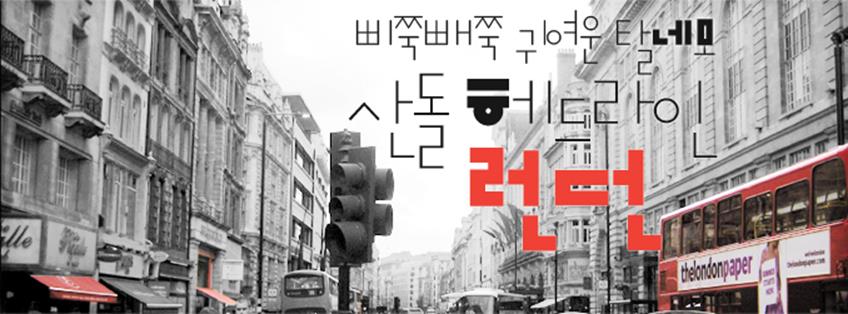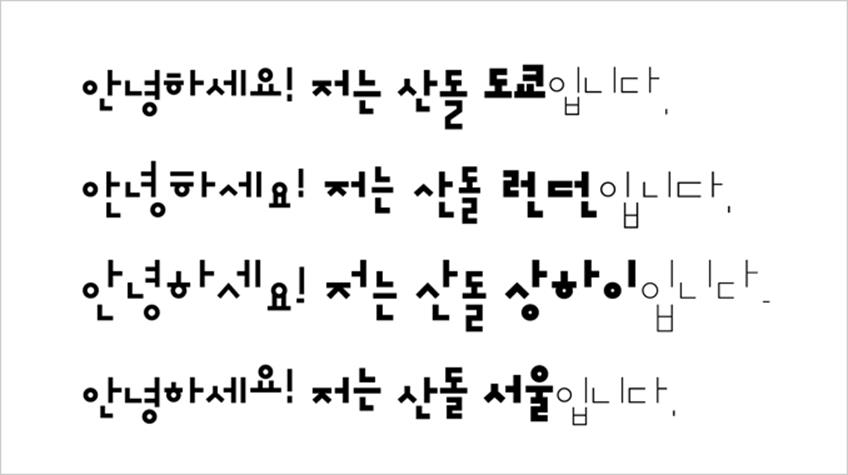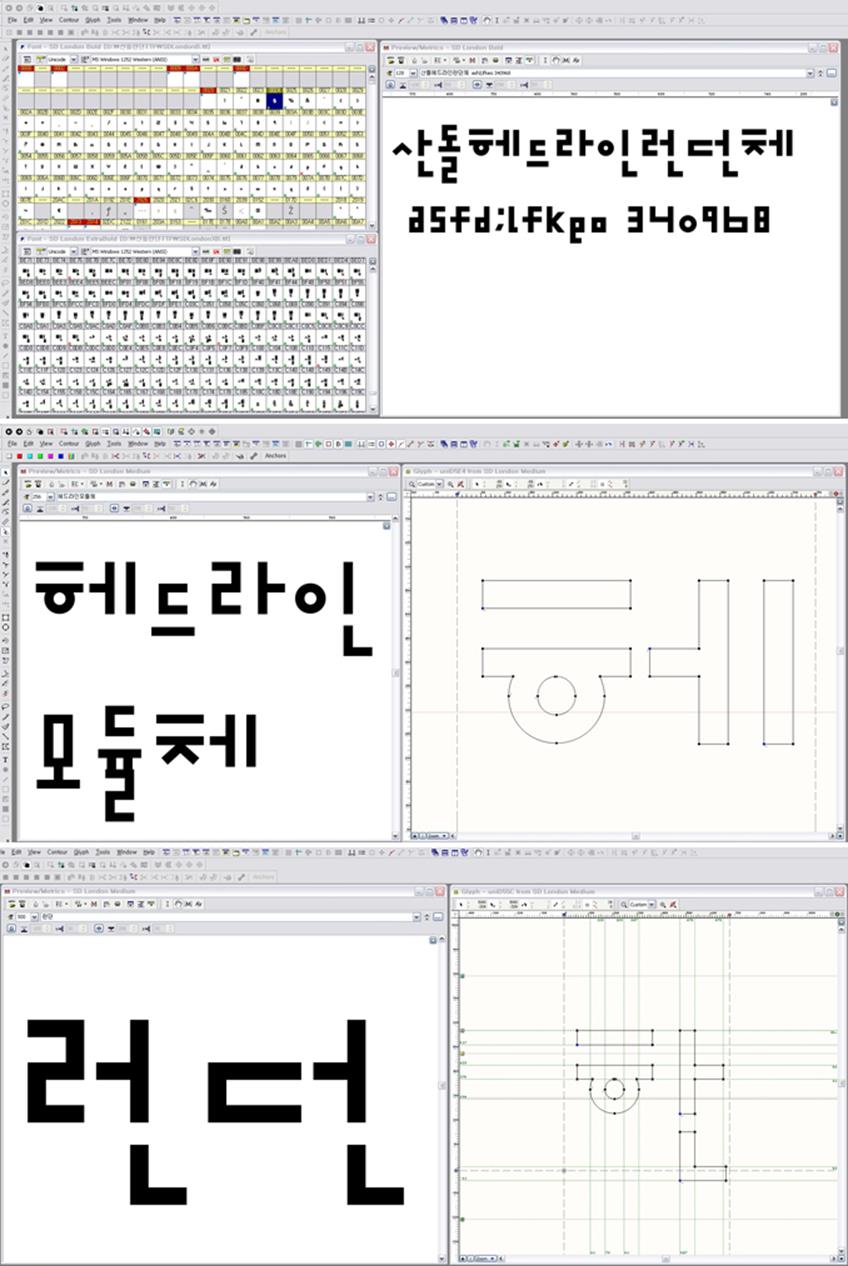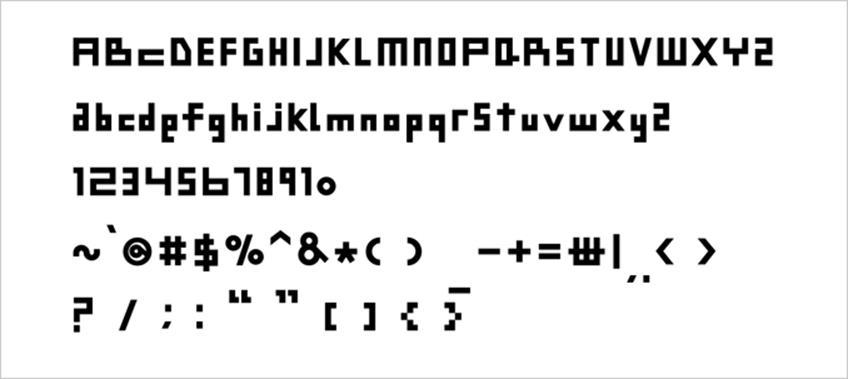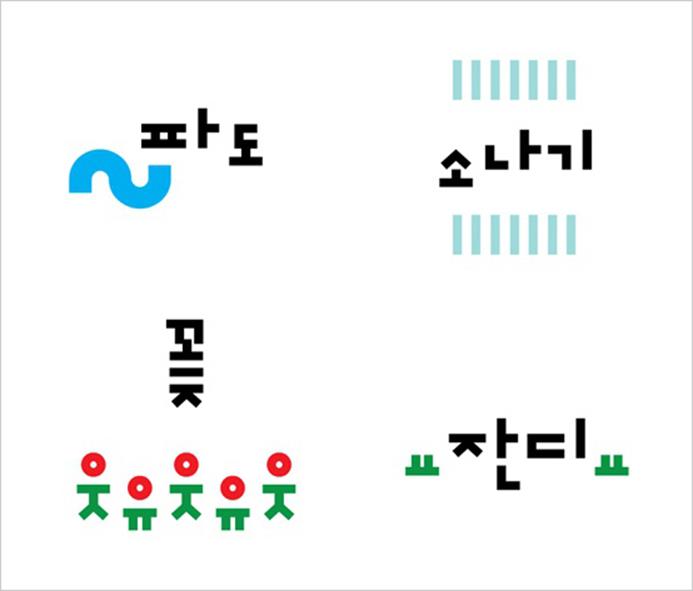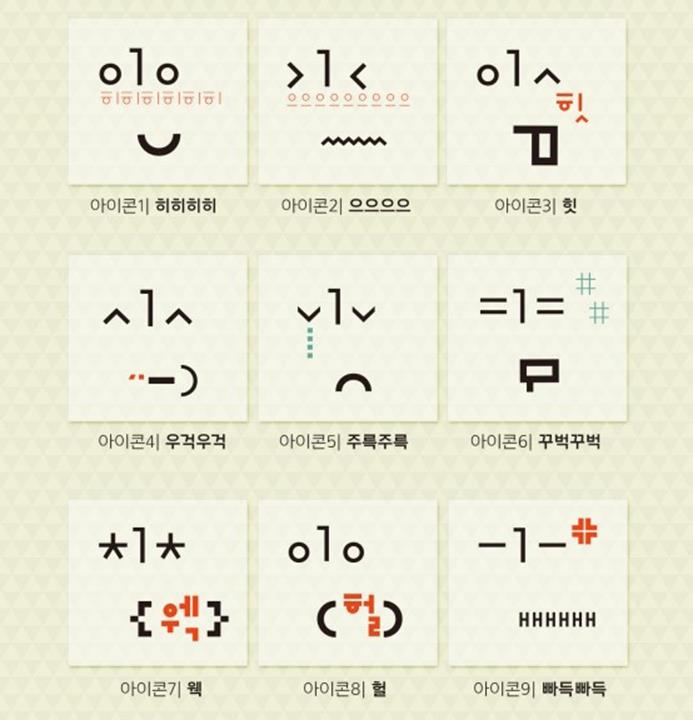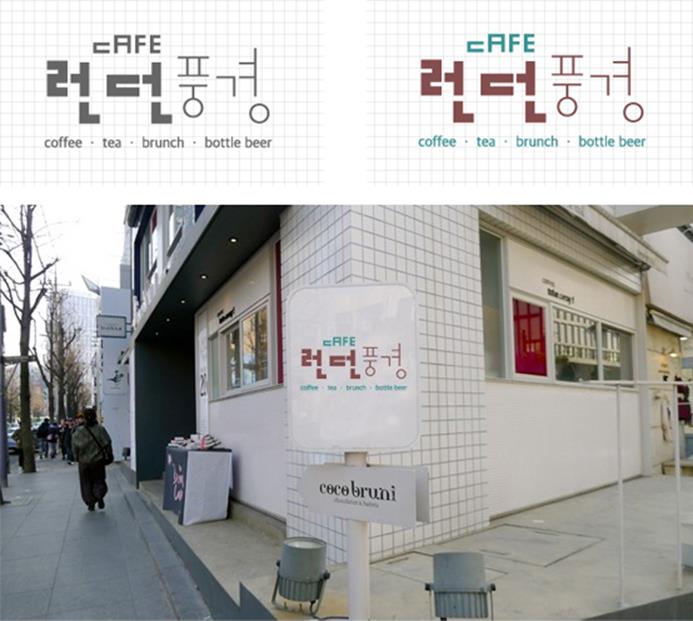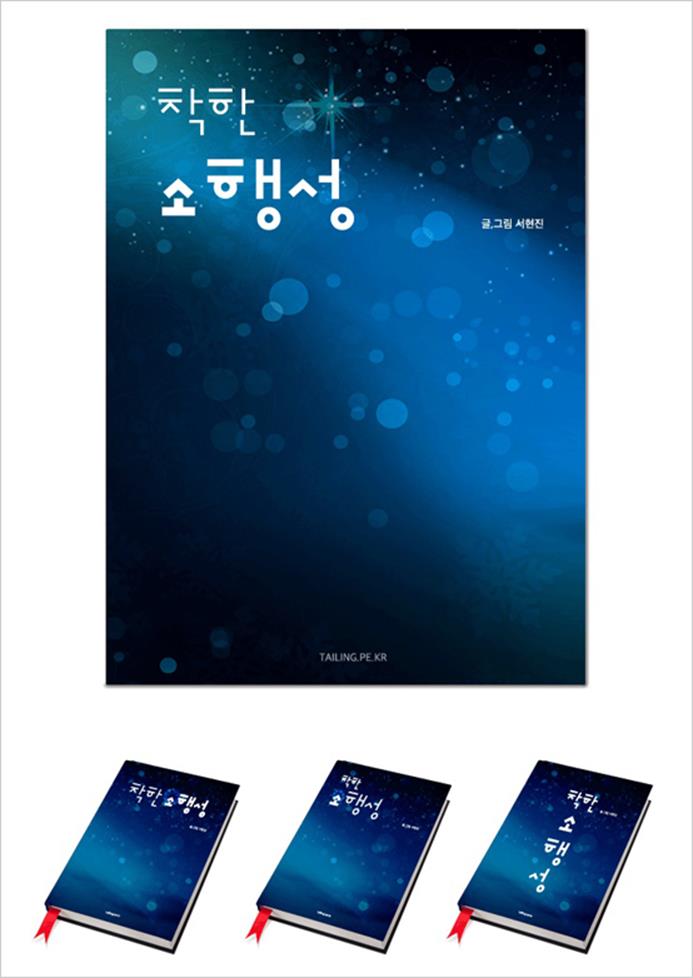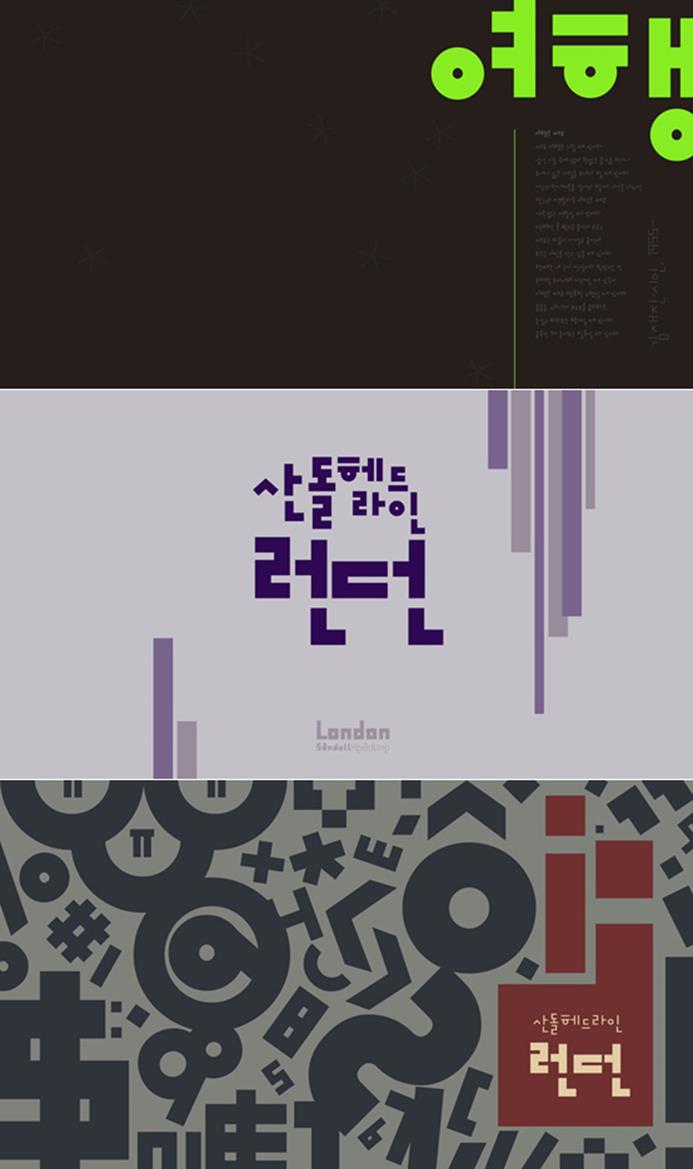
삐쭉빼쭉 귀여운 탈네모, 산돌 헤드라인 런던
산돌 헤드라인 런던은 이전에 제작된 도쿄, 상하이, 서울체에 이어 ‘시티체’ 컨셉으로 제작된 네 번째 시리즈 폰트다. 산돌 헤드라인 런던을 디자인한 송미언 디자이너로부터 런던에 대한 이야기를 들어보았다.
산돌 헤드라인 런던은 어떤 폰트인가요?
‘산돌 헤드라인 런던'(이하 런던)은 로마시대에 성벽으로 둘러싸였던 현재의 런던탑 모양을 형상화해 그리드를 살리고, 현대적이고 독창적인 탈네모꼴의 기하학적인 형태로 디자인한 서체에요. 또한 자소 크기를 길고 짧음의 변화에 초점을 맞추어 디자인해 규칙적이면서 개성 있는 느낌을 부여했습니다. 재미있는 모듈 표현과 5종의 굵기로 제작되어 잡지, 책 표지 등의 헤드라인이나 광고와 포스터 등에 다양하게 사용할 수 있는 폰트입니다.
탈네모꼴 산돌 헤드라인 런던
1. 자소 크기와 위치의 변화2. 글줄에 리드미컬한 요소 가미, 3. 자소 ‘ㅎ’의 꼭지점과 가로줄기를 동일한 길이로 표현
런던의 가장 큰 특징 세 가지를 꼽는다면요?
우선, 기존 시티체보다 자소 크기와 위치에 변화를 주어 다양한 느낌을 살렸습니다. 그리고 모듈체의 기본적인 룰을 지키면서 글줄에 리드미컬한 요소를 가미해 훨씬 생동감을 느낄 수 있게 했고요. 마지막으로 자소 ‘ㅎ’의 꼭지점과 가로줄기를 동일한 길이로 표현해 모듈체에서만 볼 수 있는 자유로운 형태를 부여했습니다.
런던 외에 서울, 도쿄, 상하이 각각의 폰트는 어떤 특징이 있나요?
‘서울’은 다양한 한글 자소의 위치 변화를 디지털화한 폰트에요. 일반적으로 ‘탈네모꼴’이라고 불리기도 하지만, 기존 서체들과 차별되는 다양한 모듈과 모음을 기준으로 한 설계가 서울만에 독특한 외형을 보여줍니다. 아시아의 중심이 된 대한민국 수도 ‘서울’의 현재와 미래의 모습이 담긴 현대적인 건물을 형상화하여 디자인했죠. ‘상하이’는 중국의 대표 도시인 상하이를 황하강에서 보이는 건물 숲의 실루엣을 형상화했고, ‘도쿄’는 서울과 모듈이 비슷하지만 글줄 및 자소 ‘ㄹ’의 개성 있는 표현으로 차별성을 두었는데요. 일본성의 동양적이면서 웅장한 모습과 기울기에서 따온 ‘ㄹ’ 형태가 적용되었습니다.
도쿄, 런던, 상하이, 서울
어떤 계기로 폰트와 도시 이름을 연결해 시리즈 폰트를 제작하게 되었나요?
리서치 결과 새로운 헤드라인 서체가 필요하다는 결론을 내리고 독특한 모듈체를 시리즈로 개발하게 되었는데요. 시티체의 가장 큰 특징은 자유분방한 모듈 형식입니다. 도심 속에 우뚝우뚝 솟아있는 건물들을 연상시켜 ‘시티체’라는 이름을 갖게 되었죠.
탈네모꼴 폰트를 제작할 때 가장 신경을 쓰는 부분은 무엇인가요?
모듈체는 제목용 이외에는 쉽게 쓸 수 없는 다양성에 대한 한계가 있어요. 가독성이나 범용성에 대한 문제점이 서체를 만들 때 가장 많이 고민한 부분이었죠. 하지만, 본문용 서체, 그래픽 서체, 모바일 전용 서체 등 다양한 성질과 특징을 가진 서체들이 그에 맞는 방식으로 사용되고 있습니다. 모듈체 또한 모듈체만의 개성을 파악해 그에 맞는 곳에 쓰여진다면 그 문제 또한 자연스럽게 해결 될 거라 생각합니다.
런던은 기존 시티체 시리즈와 잘 융합될 수 있도록 하는 것이 가장 큰 문제였다. 다행히 서울, 도쿄, 상하이와 동질감을 가지되 차별성도 함께 볼 수 있는 서체로 제작되었다.
산돌 헤드라인 런던 영문, 숫자, 기호
런던은 안상수 선생님의 마노체와 닮아 보이는데요. 어떤 차이가 있나요?
우선, 모듈체라는 점에서 같은 분류의 서체이기 때문에 얼핏 유사하게 보일 수 있습니다. 하지만, ‘ㅁ’과 ‘ㅎ’ 등의 자음 형태가 확연히 다르고 윗선, 밑선, 무게중심선이 다릅니다. 서체의 얼굴은 ‘무게중심선’ 즉, 아래, 위, 중간 중에서 글자의 중심이 어디에 있느냐에 따라 크게 바뀝니다. 탈네모꼴, 네모꼴의 성향도 결정짓게 되는데요. 자소의 특별한 장식 즉, 굴림, 꺽임, 세리프 유무 등이 없어도 이런 모듈과 그리드의 변화만으로도 기본적으로 그 글자의 고유한 색을 갖게 됩니다. 우리가 흔히 보는 수많은 고딕체와 명조체가 대부분 비슷하게 보이지만 모두 다른 디자인의 서체인 것처럼 마노체와 런던은 모듈체 특징상 유사해 보일 수는 있겠죠. 하지만 그리드의 화려한 변화로 무궁무진하게 끝없이 발전 가능한 것이 모듈체입니다. 비슷한 듯 하지만 오묘하게 각자의 얼굴을 품고 있는 것이 모듈체의 매력이겠죠.
시티체의 다음 시리즈 제작도 예정되어 있나요?
아직 구체적인 계획은 없지만 조금 더 다양한 서체를 개발해 출시 할 수 있는 기회가 있다면 진행 할 수도 있습니다.
산돌헤드라인 런던 활용 사례
디자인. 이가람 산돌파트너 3기
“1음절이나 2음절 단어만으로 엽서를 디자인해 보았다. 어떤 디자인을 해볼까 고민하다 산돌 헤드라인 런던은 애초에 헤드라인 서체로 만들어졌기 때문인지 단어로 썼을 때 굉장히 예뻐 보였다. 자음과 모음, 특수 문자를 이미지 요소로 활용해 단어를 표현하는 방법으로 접근한 것이다. 본문용으로 길게 사용하는 데는 한계가 있지만, 헤드라인 서체로는 활용도나 만족도가 높아 보인다.”
디자인. 김지윤 산돌파트너 3기
“모음의 가장 왼쪽라인에 맞추어 받침이 내려오는 것에 착안해 산돌헤드라인 런던으로 귀여운 이모티콘을 디자인했다. 일반적인 본문용 글꼴을 보면 네모틀에 맞게 글씨가 꽉꽉 채워지기 때문에 받침에 쓰이는 ‘ㅁ’이 납작하게 변한다. 반면, 마노체나 런던체는 형태가 변하지 않기 때문에 빈 공간이 많이 생기게 되는데 마노체는 세로가 긴 네모틀 안에 들어가 있다고 볼 수 있고 런던은 공간을 많이 차지하는 자음이 밑으로 더 길게 내려와 네모틀 자체를 깨버린다는 차이가 있다. 전혀 규칙 없이 자유분방한 글꼴이 아니라 자유로움 속에 나름의 규칙이 숨어있는 글꼴이라고 볼 수 있다. 마노체와 비교해보면 런던이 조금 더 꽉 찬 느낌이 강하다. 모음 길이도 다르고 글을 썼을 때 자소의 높이 변화도 다르다. 글자 간격도 런던이 더 정교하게 다듬어져 있다.”
디자인. 서현진 산돌파트너 2기
“산돌 헤드라인 런던의 디자인 컨셉에 맞춰 ‘런던 풍경’이라는 이름의 카페로고를 디자인했다. 신사동 가로수길에서 찍어왔던 사진 위에 로고를 디자인해 살짝 올려보았다. 워낙 독특한 디자인과 크기 배열을 가지고 있어 특별한 추가 작업 없어 굵기 조절만 해도 평범치 않은 느낌을 준다. 두 번째 작업은 평소에 생각해 두었던 <착한 소행성>이라는 제목으로 책 표지를 디자인해 보았다. 신기하게도 소행성의 ‘소’자가 자동으로 작은 사이즈로 입력되고 ‘착한’이라는 글자 모양도 제목의 의미와 잘 어울려 보인다.”
디자인. 이헌제 산돌파트너 3기
“산돌 헤드라인 런던을 활용해 세 개 디자인(문장, 타이틀, 기호) 작업을 해보았다. 첫 번째는 김재진 시인의 시로 문장을 적어보았는데 본문용 서체처럼 쭉쭉 적어내기는 다소 힘들지만 시처럼 짤막짤막하게 끊기는 텍스트들은 어느 정도 보는데 불편함은 없다. 두 번째는 본래 산돌 헤드라인 런던의 탄생 목적에 따라 타이틀을 디자인해 보았다. 개인적으로 ‘런던=보라색’이라는 생각이 있어 보라색을 선택하고 직사각형 그래픽 이미지를 추가했다. 마지막 세 번째 작업은 기호만으로 구성해 본 것이다.”